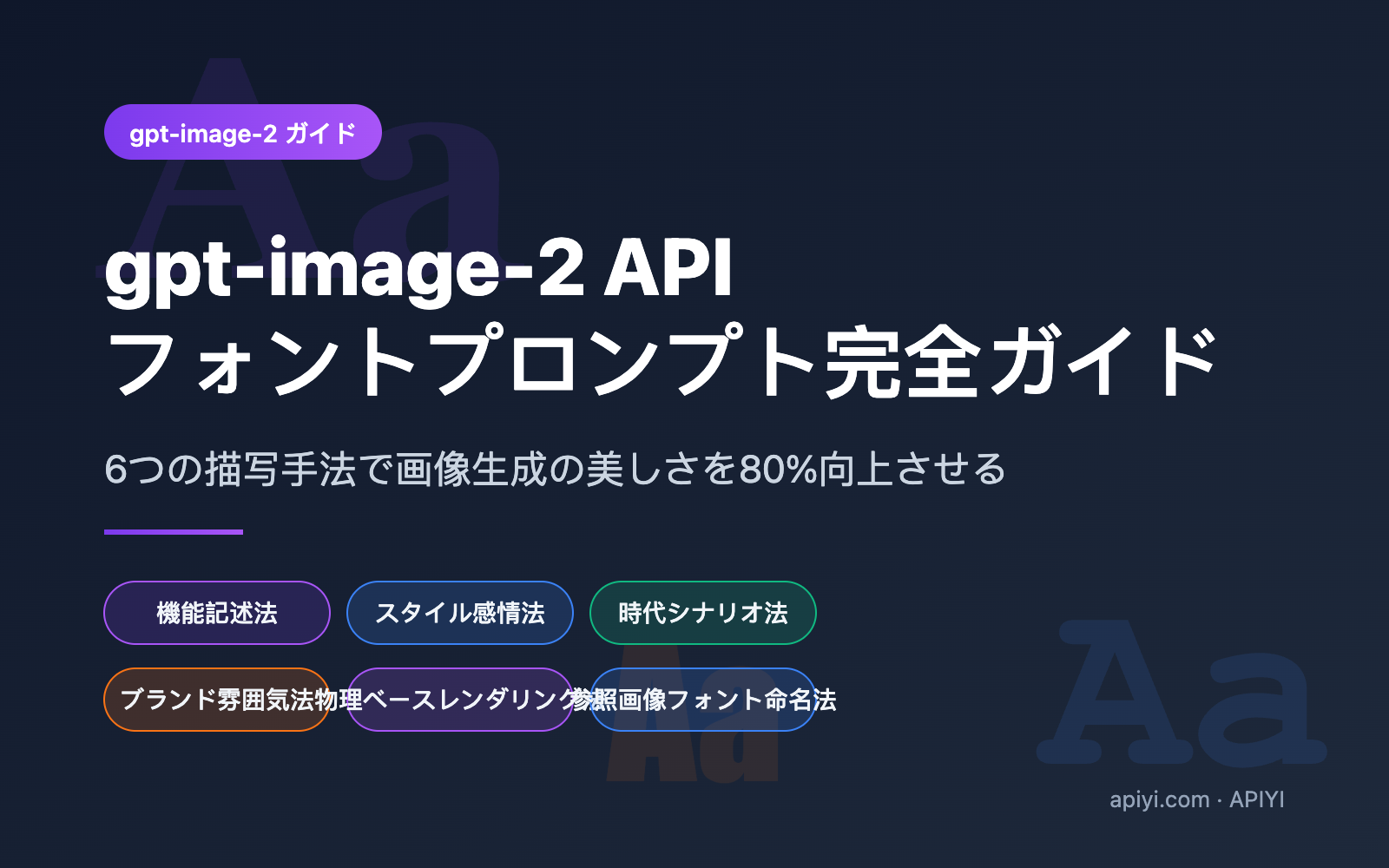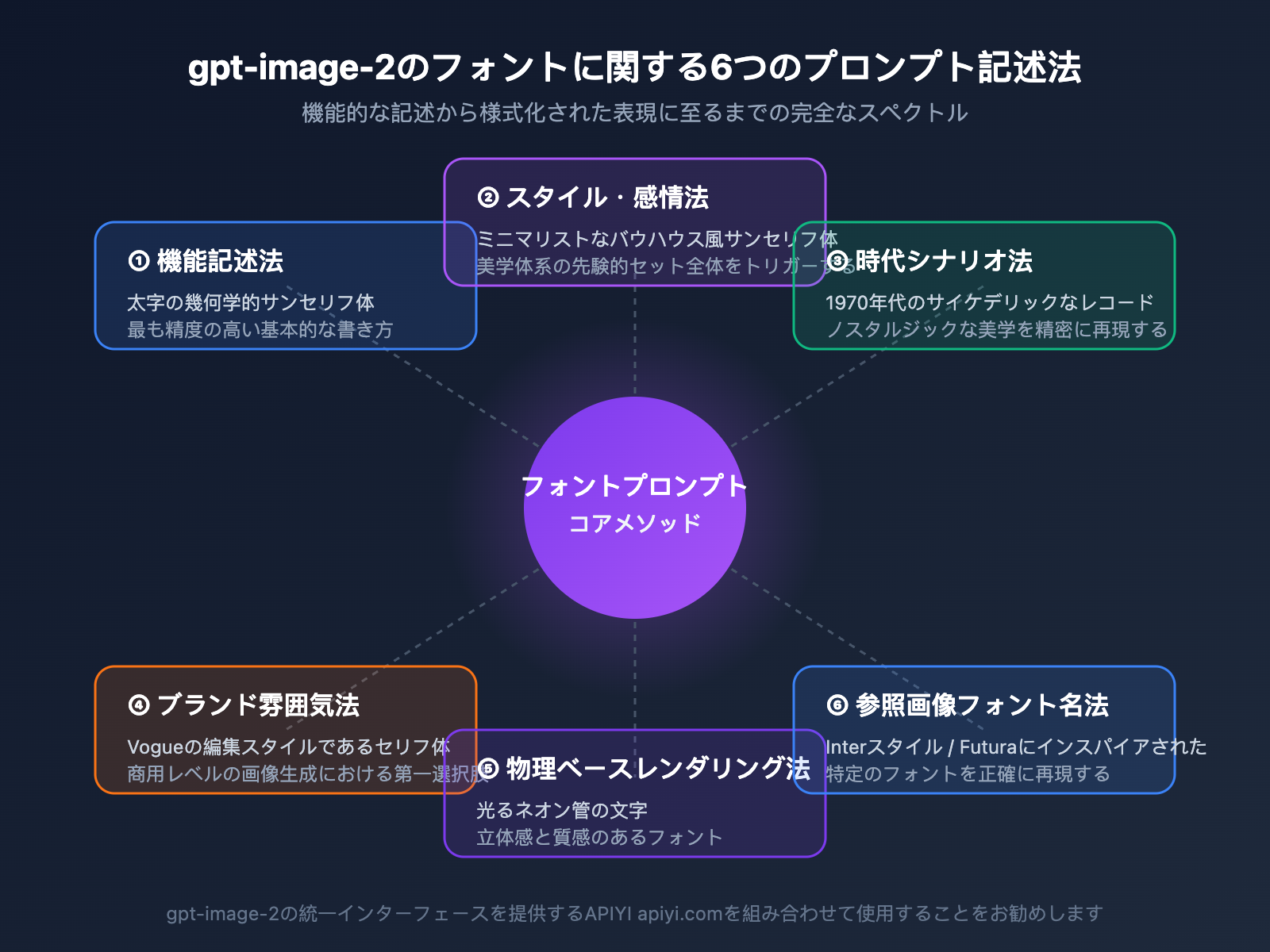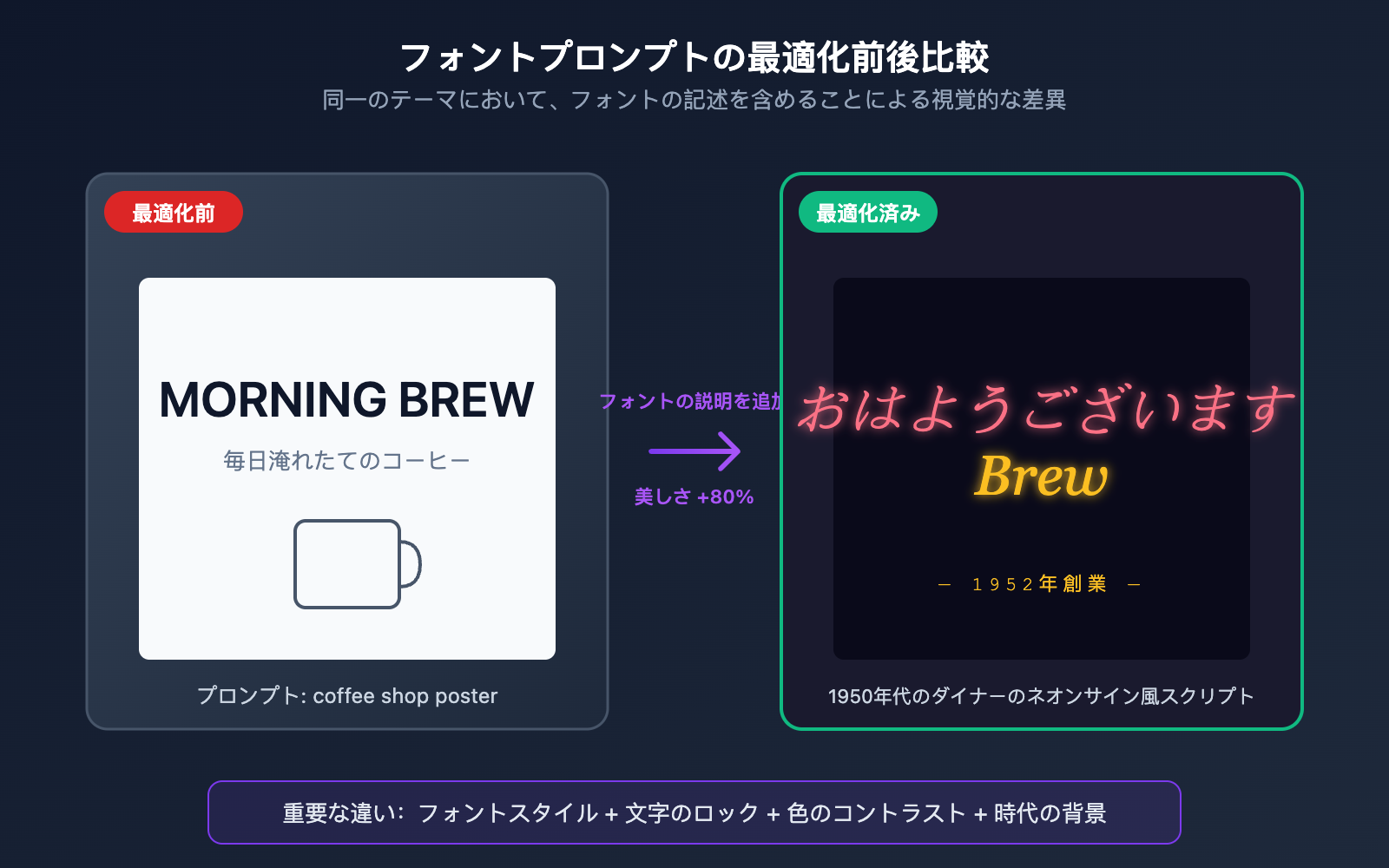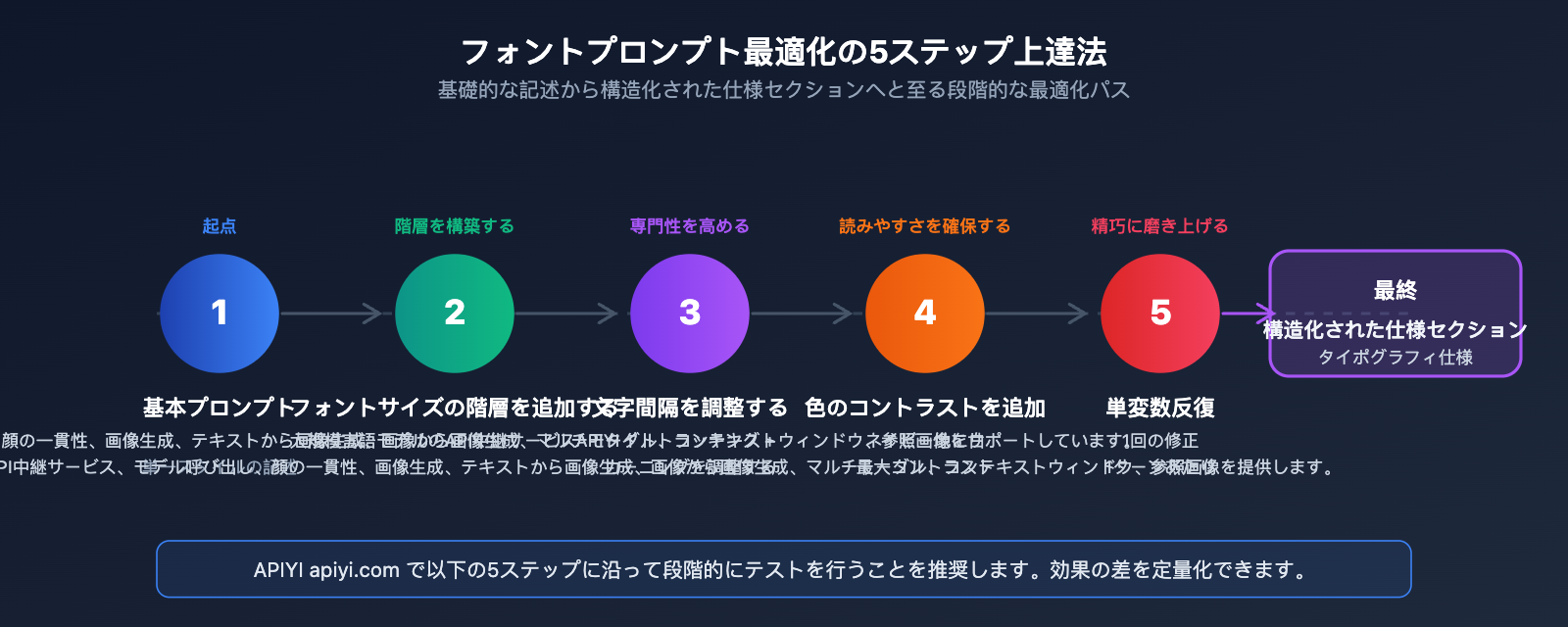
gpt-image-2 API フォントプロンプト完全ガイド:美しさを80%向上させる6つの記述法
gpt-image-2 API や ChatGPT の公式サイトで画像生成を行う際、多くのユーザーが共通の悩みを抱えています。それは、生成される画像の文字認識精度は高いものの、フォントが常に「エンジニアの美学」を感じさせる質素なサンセリフ体になってしまい、ブランド感やデザイン性に欠けるという点です。この「質素な美学」は、ポスターやSNSのカバー画像、製品プロモーション画像を作成する際に特に目立ち、せっかくの優れた構図も安っぽく見せてしまいます。
問題の根源はモデルの能力不足ではなく、大多数のユーザーがプロンプトで「何を描くか」は記述していても、「フォントがどのような見た目であるべきか」をモデルに伝えていないことにあります。本記事では、OpenAIの公式Cookbookと複数のAPIサービスでの実測経験に基づき、gpt-image-2のフォント用プロンプトの仕組みを体系的に解き明かします。そのまま使える6つのフォント記述テンプレートを提供し、APIYI(apiyi.com)プラットフォームでの呼び出し例を交えながら、5分で「美感のある」フォントを生成するためのプロンプトの書き方を解説します。
一、gpt-image-2 フォント用プロンプトの核心メカニズム
1.1 なぜデフォルトのフォントは常に質素なサンセリフ体なのか
gpt-image-2は、明確なフォントの記述がない場合、学習データの中で「最も安全」な視覚的先験知識に基づいてフォントを生成します。その結果、InterやHelveticaスタイルに近い、中立的な幾何学的サンセリフ体になりがちです。これは認識率を保証する一方で、スタイリッシュな表現を犠牲にしています。
OpenAIの公式プロンプトガイドでは、モデルはユーザーが能動的に制約を与えた視覚属性のみをレンダリングし、制約のない部分はすべてデフォルト値に従うと明記されています。つまり、単に「a poster about coffee(コーヒーについてのポスター)」と書くだけでは、モデルは最も一般的なフォントを選択します。「hand-lettered display serif with thick brushstrokes(太い筆致の手書き風ディスプレイセリフ体)」といった詳細な記述があって初めて、モデルは対応するフォントの先験知識を呼び出すのです。
これが、同じテーマ、同じプロンプトの長さであっても、フォントの記述があるかないかで生成物の品質が大きく変わる理由です。この点を理解すれば、「フォントが質素である」ことはモデルの欠陥ではなく、ユーザーがフォントを画像の中核情報として記述していないことが原因だと分かります。
もう一つ見落とされがちなのがモデルのバージョンです。gpt-image-2は1.5世代と比較して、文字レンダリング層が大幅にアップグレードされており、ネイティブで4Kに近い出力をサポートしています。小さな文字、密集したレイアウト、複数のフォントの混在処理能力が著しく向上しており、これはgpt-image-2においてフォント用プロンプトに注力する価値が非常に高いことを意味しています。
1.2 gpt-image-2 フォント用プロンプトの4つの核心要素
「フォントの記述」という作業を分解すると、gpt-image-2は実際には4つの独立した次元の指示に応答しています。どれか一つでも欠けてはいけません。
要素 役割 記述例
フォントスタイル (Style) 字形構造と視覚的な性格を決定 bold sans-serif、condensed serif、hand-lettered display
フォントサイズ階層 (Hierarchy) 見出し/小見出し/本文の対比を制御 large headline, small body copy
色のコントラスト (Contrast) 背景に対する文字の可読性を決定 high contrast white on navy
空間レイアウト (Placement) 文字の位置と配置方法を固定 centered at top, clean kerning
1.3 文字列を確実に反映させるための制約テクニック
OpenAI Cookbookの「image-gen-models-prompting-guide」では、重要なテクニックが紹介されています。それは、画面に表示させたい文字列を引用符("")またはすべて大文字で囲むことです。これにより、モデルはこの部分を「字面通りにレンダリングしなければならない、誤字脱字は許されない」という強力な制約として理解します。
実測比較の結果、「the word coffee on a sign」と書くよりも、「a sign with the EXACT text "COFFEE"」と書く方が、スペルミスの発生確率が大幅に低くなることが分かりました。後者はほぼ確実に文字レベルの一致を保証します。綴りが難しいブランド名(例:Schønne、APIYI)の場合は、スペースを空けて一文字ずつ記述すること(例:「"A P I Y I"」)を推奨します。これにより、文字の並び順のミスをさらに減らすことができます。
2. gpt-image-2のフォントプロンプト:6つの実践的な記述法
シーンによって最適なフォントの記述戦略は異なります。以下に挙げる6つの方法は、OpenAIの公式サンプル、fal.aiでの実測事例、およびオープンソースのプロンプトライブラリから抽出した、汎用性の高いテンプレートです。
2.1 機能記述法:最も安定した基本形
タイポグラフィの専門用語を使って字形の特徴を記述する方法です。OpenAIが最も推奨しており、命中率が非常に高い手法です。
• bold geometric sans-serif(太字の幾何学的サンセリフ、テック系ブランド向け)
• condensed sans-serif with tight tracking(コンデンス体、雑誌のタイトル向け)
• classic transitional serif with fine hairlines(クラシックなトランジショナル・セリフ、高級品・出版物向け)
• rounded humanist sans-serif(丸みを帯びたヒューマニスト・サンセリフ、子供向け・親しみやすいブランド向け)
2.2 スタイル・情緒法:フォントに「性格」を与える
具体的なフォント名ではなく、芸術運動やデザインスタイルを指定することで、モデルが持つ美学体系の先験的知識を呼び起こします。
• minimalist Bauhaus sans-serif
• Art Deco display typography with metallic strokes
• brutalist concrete typography
• Memphis-style 80s display font with bold geometric shapes
この方法の利点は、フォントが孤立せず、モデルが自動的に調和する色、レイアウト、装飾要素を補完し、画像全体のデザイン言語が統一される点です。
2.3 時代・シーン法:懐古的な美学を再現
年代と媒体を組み合わせることで、特定の歴史的時期の印刷物からスキャンしたかのような質感を再現します。
• 1970s vinyl record cover psychedelic display font
• 90s grunge zine handwritten typography with photocopy texture
• early 2000s Y2K chrome bubble font
• 1950s diner neon sign script lettering
この方法は、レトロ、ヴィンテージ、アンダーグラウンド文化をテーマにしたカバー画像に特に有効で、単に retro font と書くよりも遥かに高い精度で生成できます。
2.4 ブランド雰囲気法:ビジネス向け画像生成の最適解
ターゲットとする業界の視覚的な雰囲気を直接記述することで、モデルを洗練された商用フォントの規範に自動的に近づけます。
• editorial fashion magazine serif typography, Vogue style
• tech startup landing page typography, clean and confident
• luxury skincare branding typography, refined and minimal
• craft brewery label typography, hand-drawn rustic feel
2.5 物理材質法:フォントを「立体的に存在」させる
フォントを単なるデジタルレイヤーではなく、現実世界の物理オブジェクトとして扱います。これはfal.aiのチュートリアルでも強調されている高度な手法です。
• plastic letter board with uneven letter spacing, one missing slot
• glowing neon tube letters with visible glass tubing and cables
• cut paper letters with soft drop shadows, layered cardboard
• chiseled marble inscription with deep shadow inside the cuts
この方法で生成されたフォントは、光の反射、影、摩耗といったディテールを伴い、平面的な貼り付け画像とは一線を画す質感を得られます。
2.6 参考フォント名法:特定の字形を精密に再現
OpenAI公式がホワイトリストを公開しているわけではありませんが、主要な有名フォント名は認識可能です。機能記述法の補助として加えると非常に効果的です。
• clean sans-serif typography, Inter style
• editorial serif similar to Playfair Display
• geometric sans-serif inspired by Futura
フォントは画像の装飾ではなく、画像の魂です。gpt-image-2 のフォントプロンプトをマスターすることは、本質的に「プロンプトエンジニアリング」を画面の構成レベルからタイポグラフィデザインのレベルへと拡張することであり、AI 画像生成が「見られるもの」から「プロフェッショナルなもの」へと進化するための重要な一歩となります。